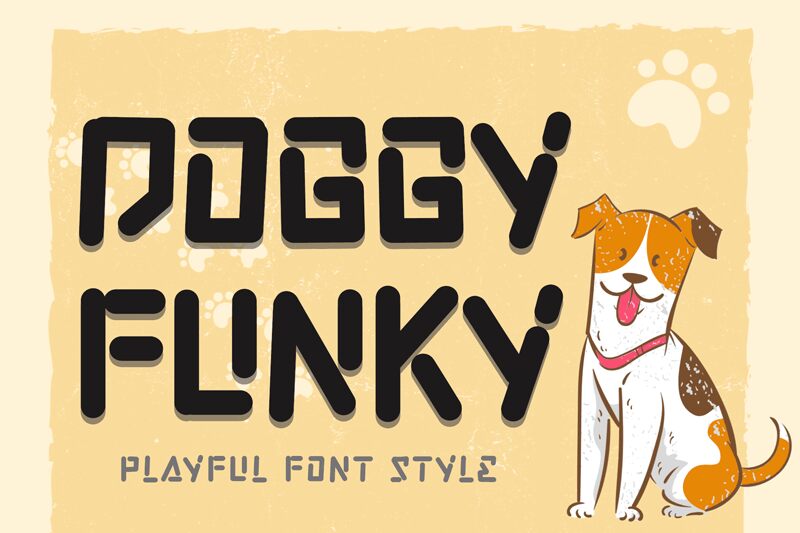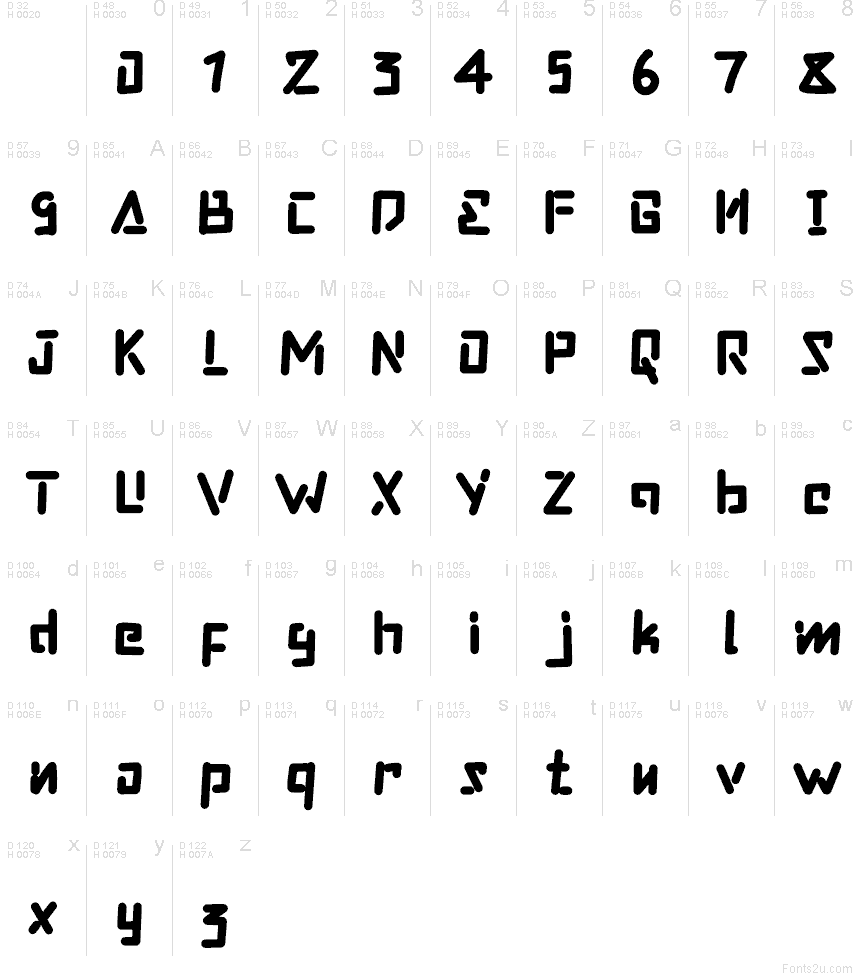
Doggy Funky Demo
Doggy Funky é uma fonte display gratuita e arredondada, com formas robustas e quadradas e cantos suaves que conferem às letras um aspecto de recorte, quase moldado. As formas repetidas mantêm o visual estável, enquanto as aberturas fechadas e os traços inferiores em gancho adicionam um toque de movimento sem parecer bagunçado.
Doggy Funky funciona muito bem para design de logotipos, títulos de cartazes, embalagens, flyers de eventos, gráficos de redes sociais e capas de álbuns, pois seu contorno claro e geometria peculiar captam a atenção em usos curtos. Esta fonte gratuita também se adequa a detalhes em cabeçalhos, sinalização de lojas e peças de branding que precisam de um estilo de letra amigável, porém fora do comum.